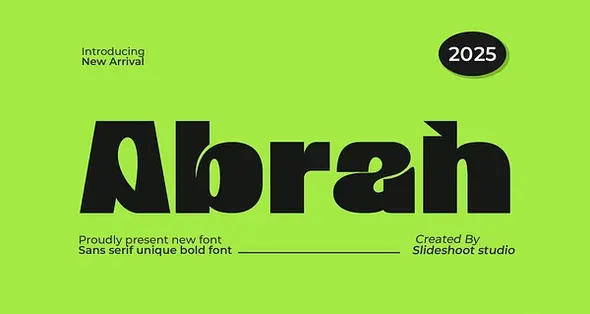
• Abrah || Unique Bold Sans Serif Font
• circle سبک قلم: Sans serif
Abrah یک فونت سان‌سریف مدرن، جسورانه و ترندی است که با حالتی بازیگوش (Bouncy) و بامزه طراحی شده است. این فونت دارای کاراکتری منحصربه‌فرد با تم چوبی است که آن را برای ترکیب با طراحی کارت‌های دعوت، لوگوی شرکت‌ها، عنوان فیلم، کارت ویزیت، نام برند و سایر پروژه‌های گرافیکی ایده‌آل می‌کند.
Introducing Abrah is a bold modern sans serif font, trendy, bouncy and cute display font. It has a unique character with wood theme. It is perfect to be combined with invitation card designs, company logos, movie titles, movie names, business cards, book titles, brand names and various other designs.